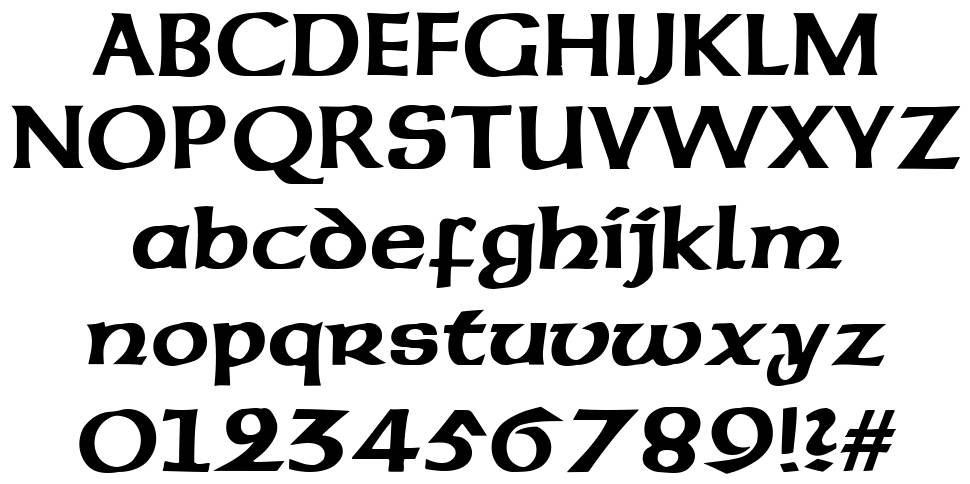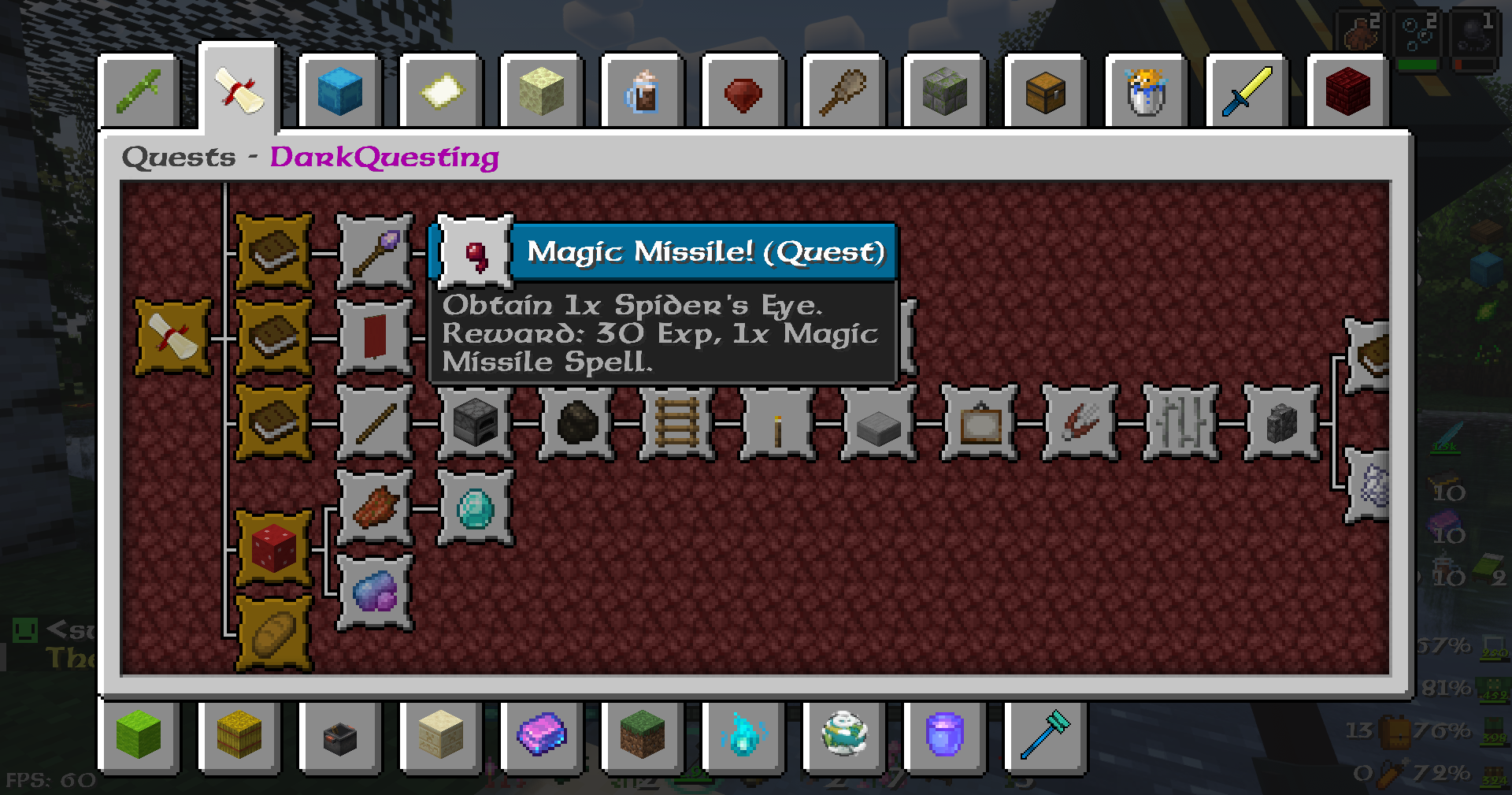
Link's Font для Minecraft: Добавляем шрифт из The Legend of Zelda в игру
Minecraft — это игра, где каждый может настроить мир под свои предпочтения. Один из способов персонализации — использование ресурспаков, которые меняют текстуры, звуки и даже шрифты. В этой статье мы рассмотрим Link's Font — уникальный шрифт, вдохновленный The Legend of Zelda: Wind Waker, который придаст вашему Minecraft-миру атмосферу приключений.
🔍 Что такое Link's Font?
Это пользовательский шрифт, созданный на основе Sherwood Font из The Legend of Zelda. Изначально он разрабатывался для модпака DarkRPG, но теперь доступен всем игрокам.
📌 Основные особенности:
✔ Стиль Wind Waker — узнаваемые буквы в духе легендарной игры.
✔ Читаемость — несмотря на необычный дизайн, текст остается разборчивым.
✔ Совместимость — работает в ванильном Minecraft без дополнительных модов.
✔ Разрешение 32x — четкие и детализированные символы.
🎮 Где лучше всего использовать этот шрифт?
Link's Font отлично подойдет для:
✅ РПГ-серверов — создаст атмосферу средневекового приключения.
✅ Карт в стиле Zelda — если вы разрабатываете приключенческие карты, этот шрифт добавит аутентичности.
✅ Ванильной игры — просто для красоты и нового визуального опыта.
🔥 Дополнительные возможности
Если вам нравится стиль The Legend of Zelda, попробуйте сочетать этот шрифт с:
- Текстурами в стиле Wind Waker (если найдете подходящий ресурспак).
- Модами на мечи и щиты из Zelda.
- Приключенческими картами, вдохновленными Хайрулом.
🏁 Заключение
Link's Font — это отличный способ разнообразить Minecraft, добавив в него частичку культовой The Legend of Zelda. Установка занимает пару минут, а эффект впечатляет! Если вы любите кастомизацию и атмосферные детали, обязательно попробуйте этот шрифт.